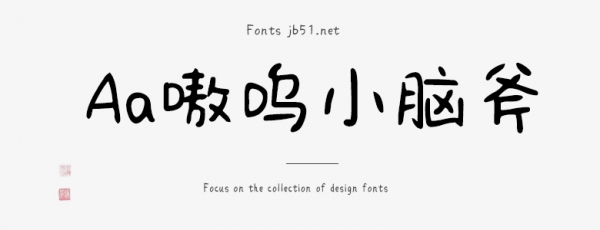
Aa嗷嗚小腦斧是一款不錯的藝術(shù)字體,由Aa字庫出品,字體筆觸適中,書寫流暢,擁有字符數(shù)22080和字形數(shù)22051,具有很好的視覺感,適合應(yīng)用于藝術(shù)設(shè)計、平面宣傳設(shè)計、網(wǎng)頁設(shè)計,書法字帖等領(lǐng)域,需要的朋友可以前來本站下載。